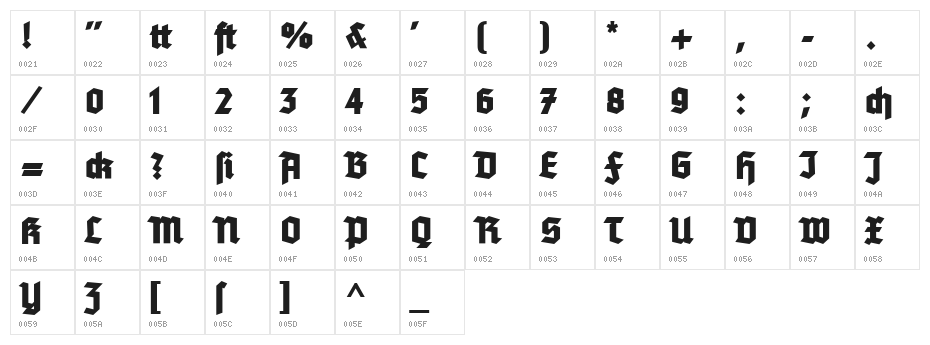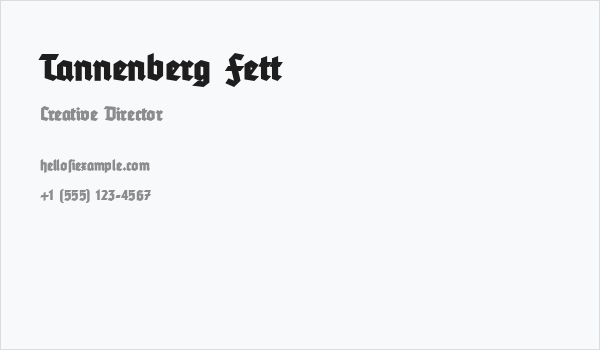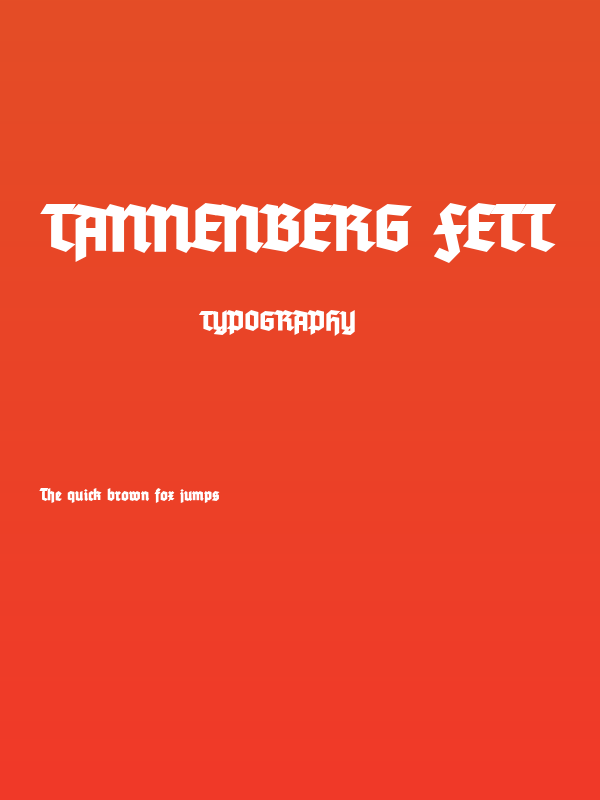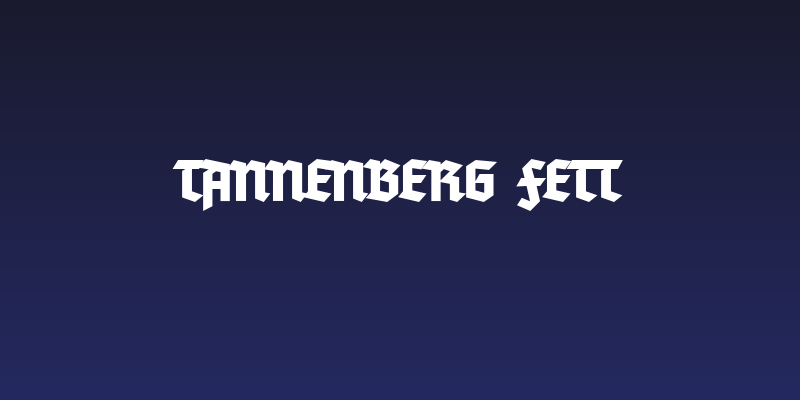
Tannenberg Fett Font
| Категория | Gothic |
| Общий стиль | Vintage |
| Рекомендуемые проекты | Ideal for projects requiring a historical or gothic aesthetic, such as posters, book covers, or branding for vintage-themed products. |